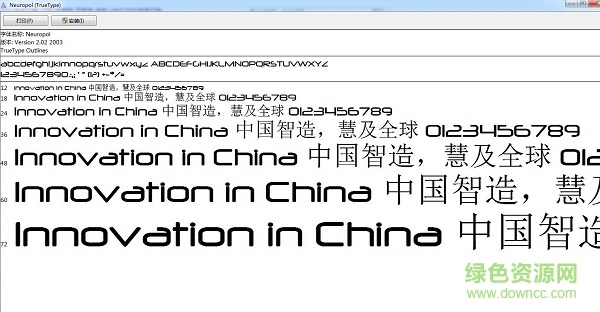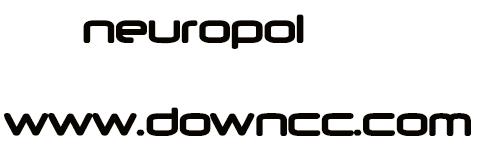
neuropol-gbpc-euc-h font
neuropol font字體包收錄了neuropol regular、neuropol bold粗體、neuropol medium等多款優(yōu)秀的字體,字形漂亮,實用性強,歡迎大家在綠色資源網(wǎng)免費下載neuropol.ttf字體!